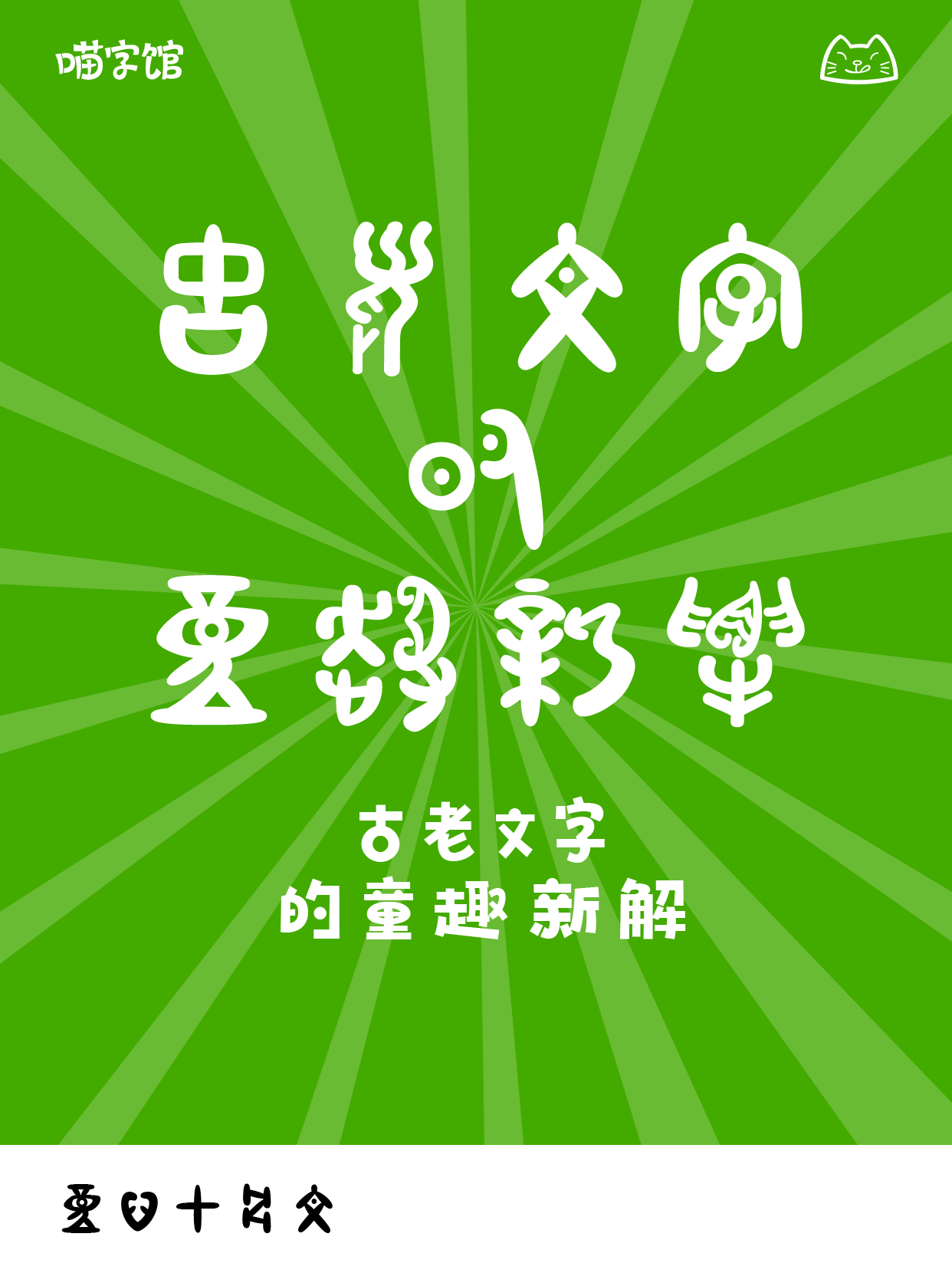
造字侠伏魔简繁 传神,
笔墨浓厚,粗细对比较为明显,字体结构较为中正,字体里笔画的“勾、提、挑、捺”等笔画特点明显、夸张,极具视觉冲击力,单字结构收放自如。
励字铁拳简 超级黑,
一款创意黑体字,笔画粗壮、字面宽大,饱满的块面感以及折角圆设计,视觉冲击强烈,犹如铁拳出击,横扫千军。
童心甲骨文,
童心甲骨文是一款定位于儿童教育行业的细分字库产品。它的整体风格轻盈、圆润,带有强烈的手写感和卡通特点。这些特点使得它非常适合用于教育相关的素材和物料。它的设计风格适合吸引孩子们的注意力,让他们更加乐于参与学习和探索。此外,童心甲骨文的字形清晰可辨,便于儿童初学者识字和书写。无论是在教室、教材、海报还是其他教育资源中使用,童心甲骨文都能为儿童教育增添趣味和活力。